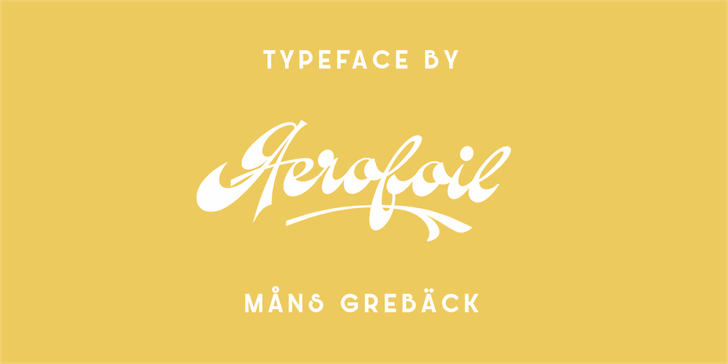
Aerofoil é uma fonte script que transmite uma sensação de elegância e sofisticação através de sua escrita fluida e delicada. Måns Grebäck, o designer desta fonte única, cria designs com um toque quase flutuante que parece fluir sem esforço da tela do computador para seu papel final. Ideal tanto para textos de texto como para design gráfico, a Aerofoil oferece uma gama incrível de caracteres em seu conjunto, garantindo que o designer possa adaptar sua ideia ao formato mais adequado para cada projeto. A fonte foi desenvolvida pelo estilista nórdico Måns Grebäck, conhecido por suas criações únicas e inspiradoras. Para esclarecer qualquer dúvida ou explorar mais sobre seu trabalho, visite o site pessoal de Måns, www.mansgreback.com, ou sua página no Facebook, @mansgreback. Recomendamos também dar uma olhada nos outros projetos incríveis do designer. Como fonte script, a Aerofoil pode ser perfeita para aplicar um toque sofisticado e único em qualquer projeto de design gráfico. Seja você um estilista digital buscando criar layouts elegantes ou um designer de revistas procurando por uma fonte que se destaque entre o resto, a Aerofoil é definitivamente um recurso indispensável no seu estojo de ferramentas digitais.
Designer: Måns Grebäck